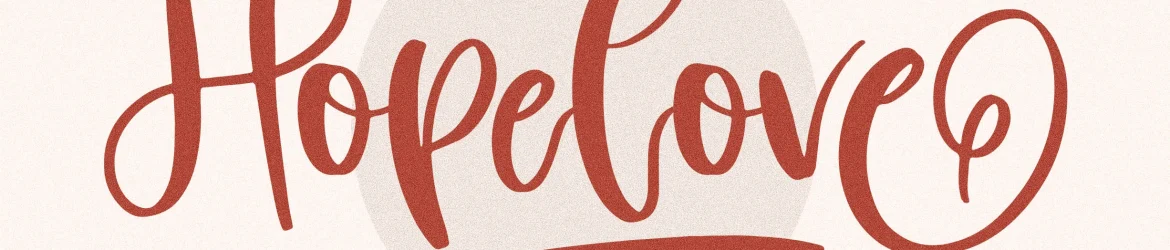
Hopelove Font
Esta é uma fonte escrita à mão perfeitamente adequada para diversos projetos que buscam aquele toque único e autêntico do handwritten. Apenas imagine a caligrafia fluída desta fonte percorrer sua página de design, trazendo vida e personalidade aos seus projetos. Sujeito a qualquer projeto como logotipos, criação de marca, designs de móveis de casa, embalagens de produtos, taças, frases, posteres, sacolas de compra, camisetas, capas de livros, cartões de nome, cartões de convite, cartões de agradecimento, etiquetas, fotografia e até mesmo marcas d’água para eventos especiais, esta fonte escrita à mão é perfeita. Além disso, ela também pode ser usada em qualquer projeto que precisa desse toque delicado e sofisticado do handwritten. Com o designer perspectype por trás desta criação única, não há dúvida de que a fonte Hopelove irá adicionar um brilho especial ao seu trabalho.